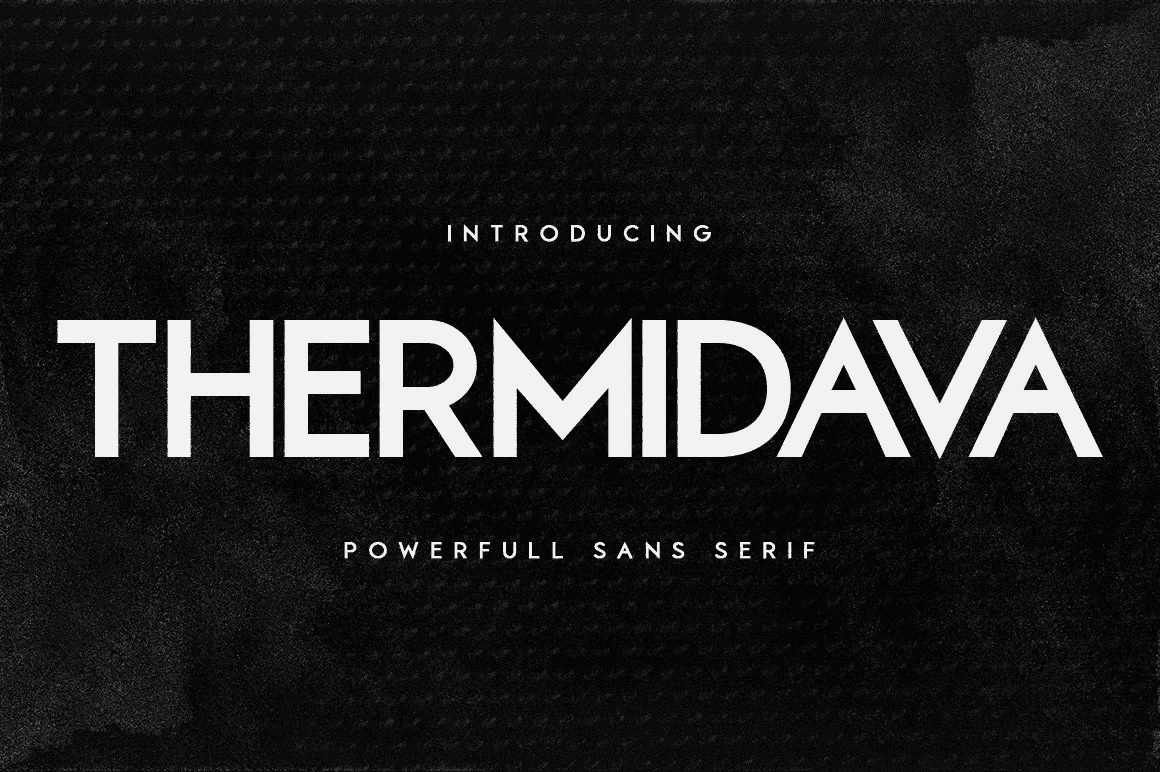
Название: Thermindava Font (2021)
Thermidava - это крутой, современный и смелый шрифт без засечек.
Его можно легко подобрать к невероятно большому набору проектов, поэтому добавьте его к своим творческим идеям и обратите внимание, как он их выделяет!
Название: Thermindava Font (2021)
Thermidava - это крутой, современный и смелый шрифт без засечек.
Его можно легко подобрать к невероятно большому набору проектов, поэтому добавьте его к своим творческим идеям и обратите внимание, как он их выделяет!